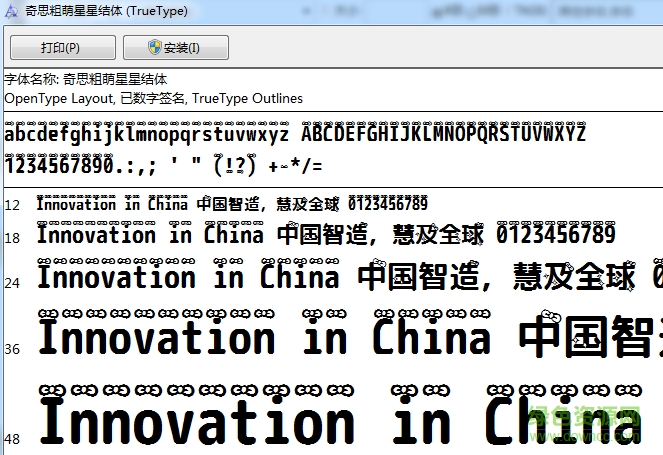
奇思星星結(jié)體字體是超萌有趣的個性字體,字體中包含有蝴蝶結(jié)和星光在里面,給用戶提供了一個非常萌系的字體,有喜歡的朋友就來綠色資源網(wǎng)下載使用吧!
奇思星星結(jié)體字體是一款別樣的字體,字體穿插的星光和蝴蝶結(jié),都是個性的象征,有需要的朋友就趕快來綠色資源網(wǎng)下載吧!